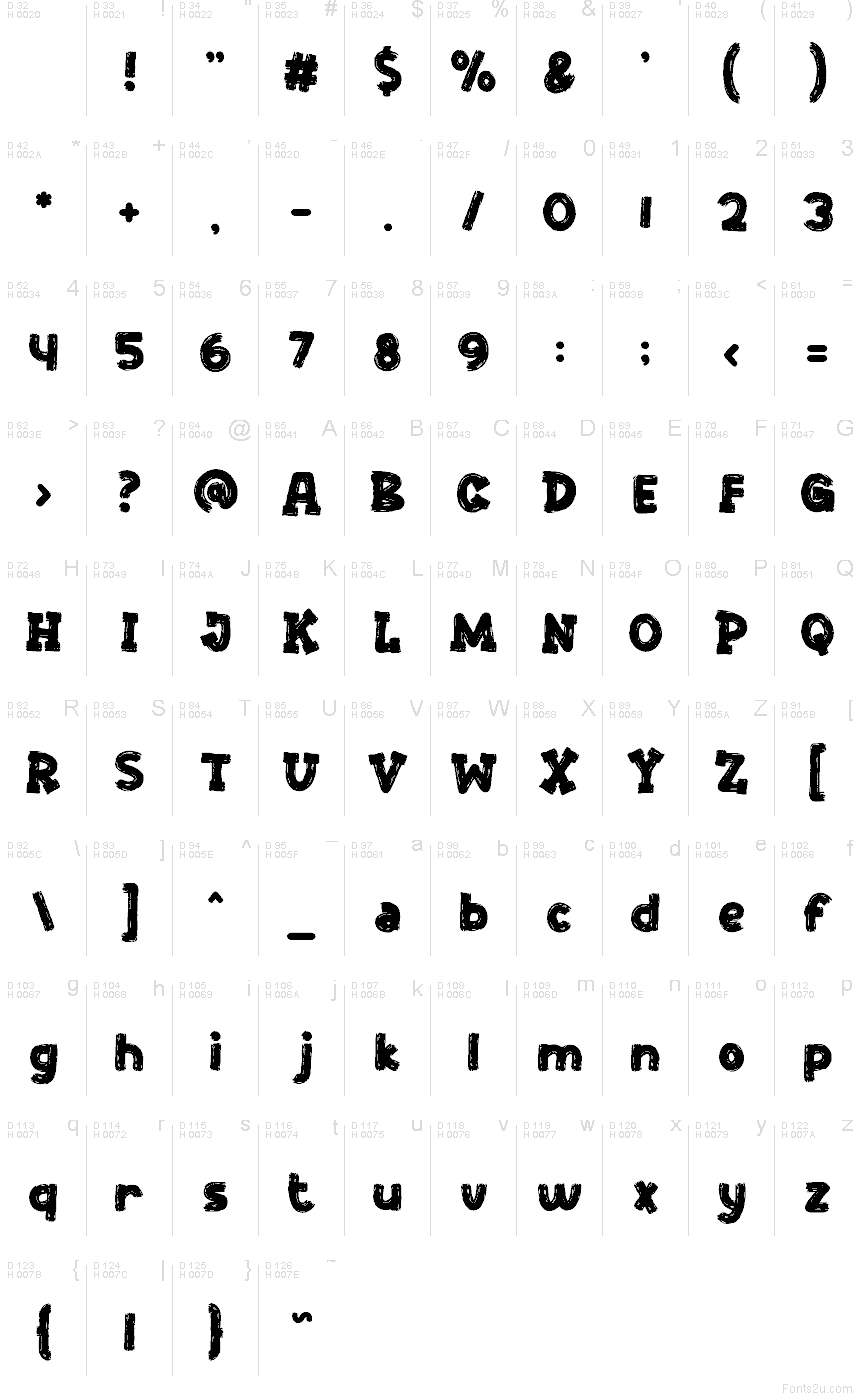
Crayon Craft Six
Crayon Craft Six od Putracetol Studio je bezplatné kreslené písmo, ktoré mení každé písmeno na hrubý, voskový čmáranec. Výplň pripomínajúca pastelku, tupé zaoblené tvary a žíhané okraje dávajú písmenám neformálnu textúru, ktorá pôsobí skôr ako rýchly plagát než ako profesionálna typografia.
Tento vzhľad sa hodí na pracovné listy pre deti, branding pre kreatívne potreby, školské plagáty, narodeninové pozvánky a miniatúry na YouTube pre rodinný obsah. Najlepšie vynikne v krátkych nadpisoch a popiskoch, kde efekt vyfarbovania dodáva jednoduchým slovám výrazný domáci tón bez potreby ďalších ilustrácií.